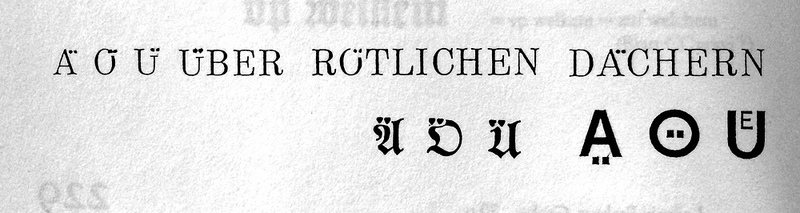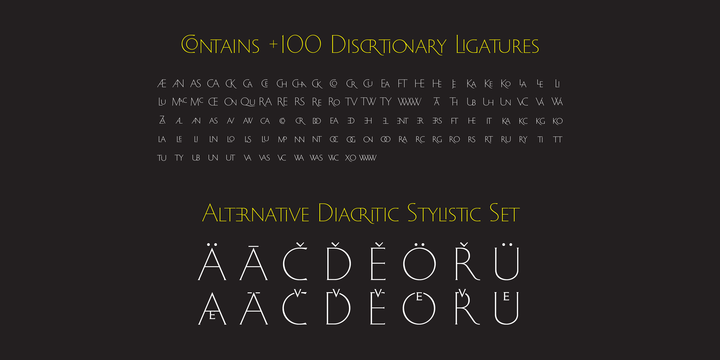
Antiqua Schrift mit Umlauten innerhalb des Versals (Ä-Ü-Ö)
kennt Jemand eine Antiqua Schrift wo die "Tüdelchen" (wie heissen die richtig, das wisst Ihr sicher) der Umlaute ÄÖÜ innerhalb der Versalien liegen, z.B. als Striche.
Ich arbeite mit eine dreizeiligen Überschrift in Versalien in der Times ohne nennenswerten ZAB, da sind die "Tüdelchen" dann in der Zeile darüber was nicht gewünscht ist. Also suche ich eine alternative Schrift wo zB. die Punkte striche sind und im AOU sind oder nur ganz wenig drüber rausragen.
ich vermute, genau da liegt der hund begraben. in den allermeisten fällen braucht es einen vernünftigen zeilenabstand, damit das ganze akzeptabel aussieht.
Ja, das ist prima, vielen Dank für den link. Die Scotch Modern asl Antiqua kommt dem ja sehr nahe.
Allerdings gibt es da kein O mit Strichen sondern nur mit Punkten rechts und links (Kunde sagt Bärchen) - geht also nicht - noch eine Idee?
Die Typoart-Garamond und die Thannhaeuser-Antiqua hatten (zumindest in der Bleisatzfassung) die Pünktchen vom Ö im O drin ...
Beide Schriften gibts auch digital, ob aber dieses Detail übernommen wurde, weiß ich nicht ...
Für deutsche Gießereien scheint das regelrecht Standard gewesen zu sein. Weniger als Alternativversion, sondern (siehe unten) gleich als entsprechend »eingezogene« Gestaltung. Alle diese Schriften sind aber nicht in der Liste der der Fonts mit Titelsatz-Umlauten, da die digitalen Versionen diese Merkmale nicht haben.
Da bei digitalen Schriften die Akzenthöhe über die Kegelhöhe hinausschießen kann, verstand man diese Gestaltungsart wohl als vermeidbare Beschränkung des Bleisatzes. Außerdem harmonieren die Umlaute-Punkte in der heute »normalen Höhe« natürlich auch besser mit allen anderen diakritischen Hütchen.
Heute mit OpenType könnte man so etwas natürlich wieder leicht als Alternative anbieten, aber spätestens seit der Zeit der 8-Bit-Zeichensätze (wenn nicht schon im Fotosatz) flogen diese Merkmale halt aus allen Schriften raus und kamen dann bei der Umstellung auf OpenType auch nicht wieder hinzu.
Da sind einige schicke Beispiele dabei – ich frage mich, warum solche Alternativen heute bei Schriften nicht öfters angeboten werden.
Auch wenn ich der Meinung bin, dass ausreichender Durchschuss der Lesbarkeit ungemein hilft.
Bei Bleisatzschriften für den deutschen Markt war es natürlich kein Problem (oder sogar technisch erforderlich), dass so zu machen. Digitale Schriften haben aber natürlich dutzende diakritische Zeichen (neben Ä/Ö/Ü). Es wäre also dann eine reine Insellösung für den deutschsprachigen Raum (wenn man nur Alternativen für ÄÖÜ anbietet), oder man muss sich für unzählige Zeichen (Circumflex, Macron usw.) etwas einfallen lassen. Da wird es dann schon kompliziert.
Man könnte so etwas aber durchaus als stilistische Alternative speziell für deutsche Umlaute anbieten, um das dann noch deutlicher vom diakritischen Zeichen und der damit gänzlich anderen Bedeutung in ë und ï zu trennen.
Ähnliches kenne ich für gebrochene Schriften, bei denen es als Alternative auch die Umlaute mit über gesetztem e gibt.
Übrigens hat ja auch die Gong, an deren digitaler Umsetzung ich derzeit dran bin, und mich darauf intensiv vorbereite, solche in die Versalien eingezogenen Umlaut-Punkte bzw. Striche (beim O) und werden diese auch digital bekommen.
Hier noch eine Abbildung aus dem Kandler, die abgelehnte Entwürfe der Beratungen von 1903 zeigt.